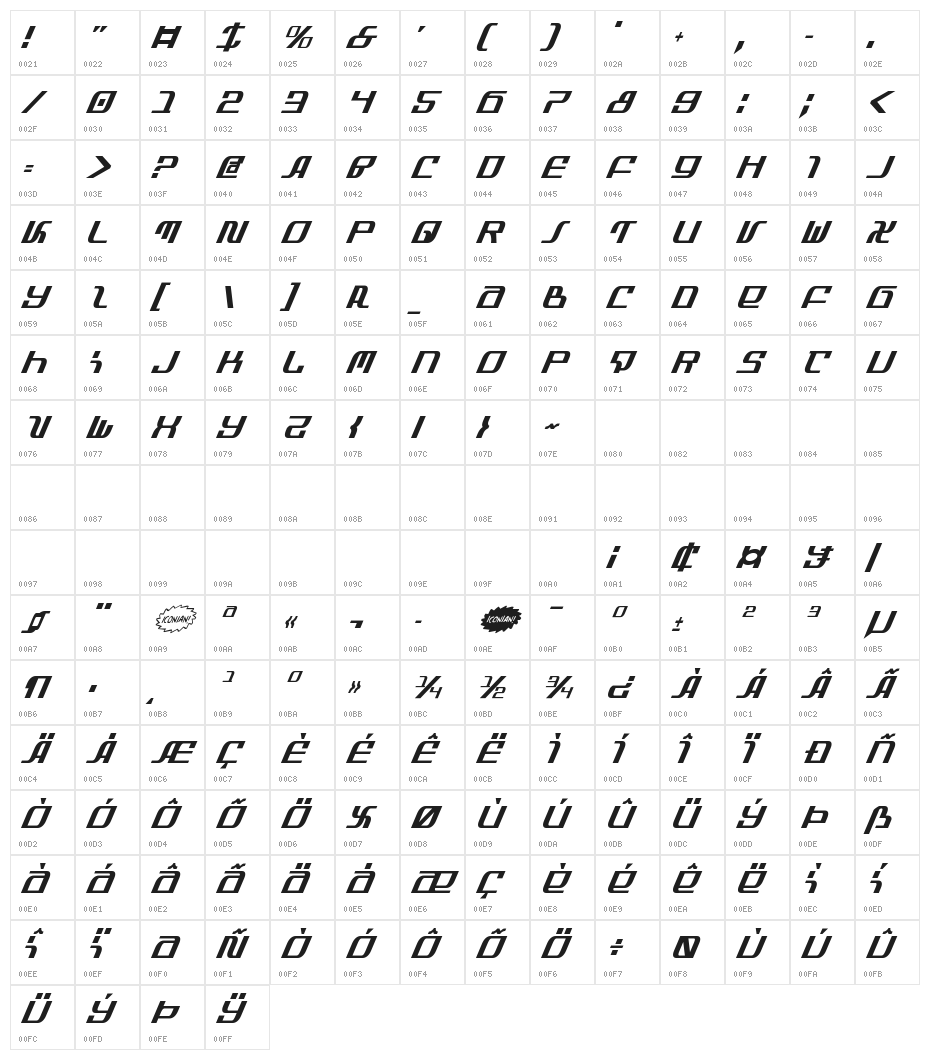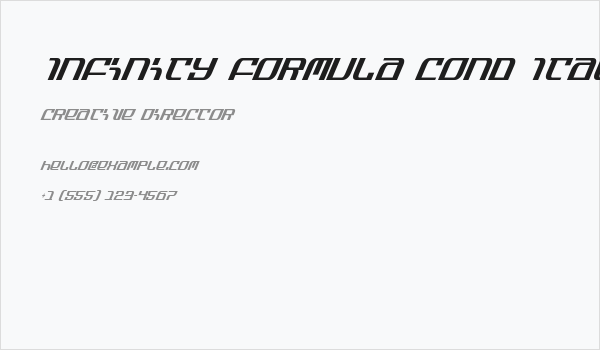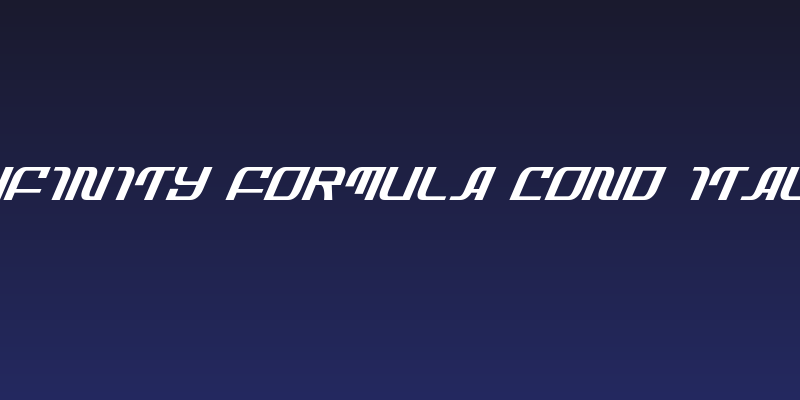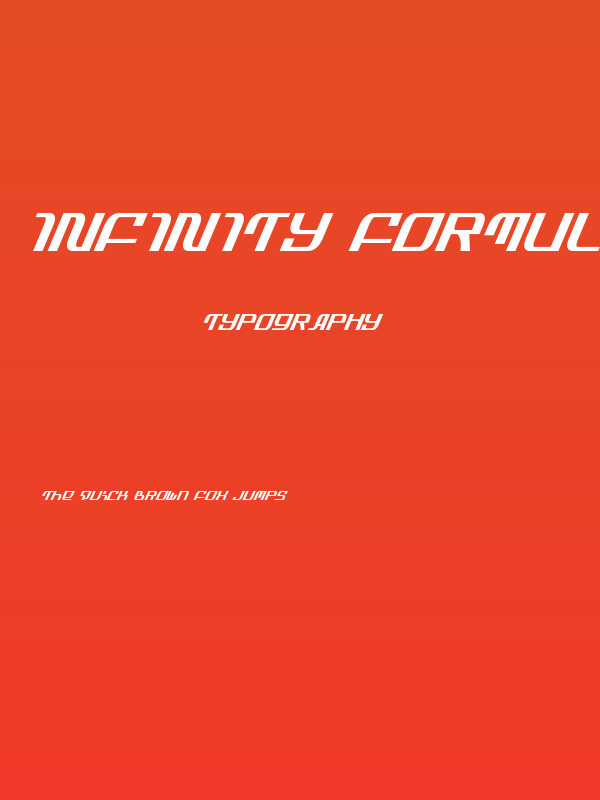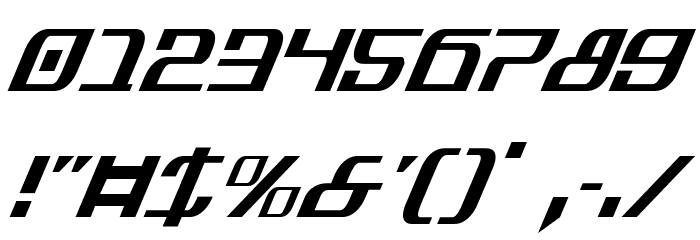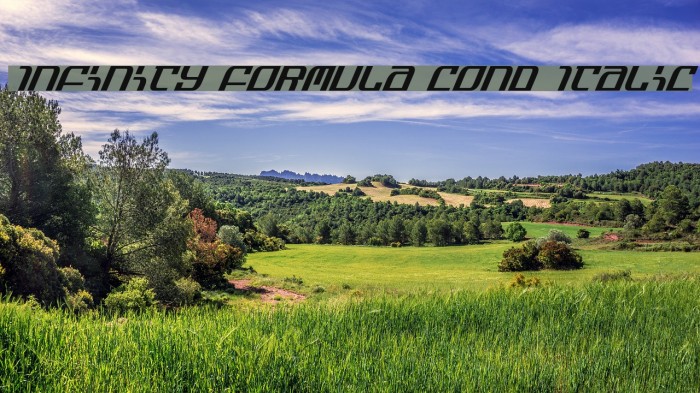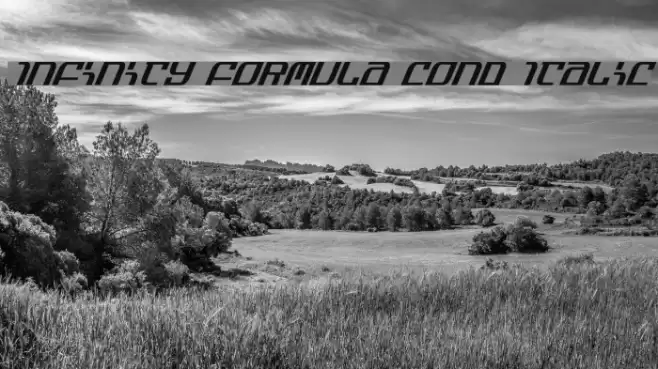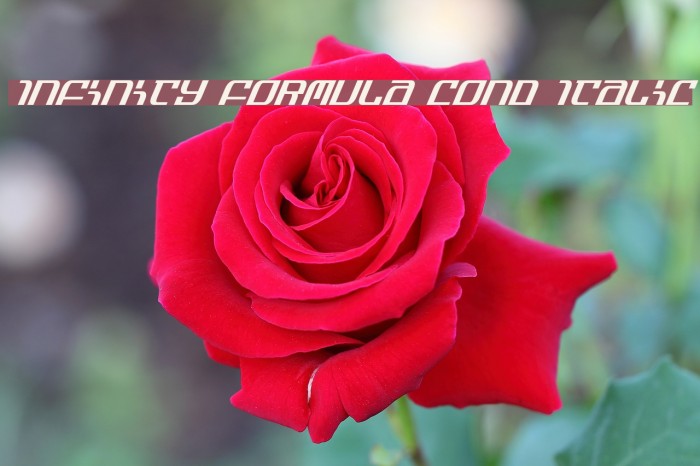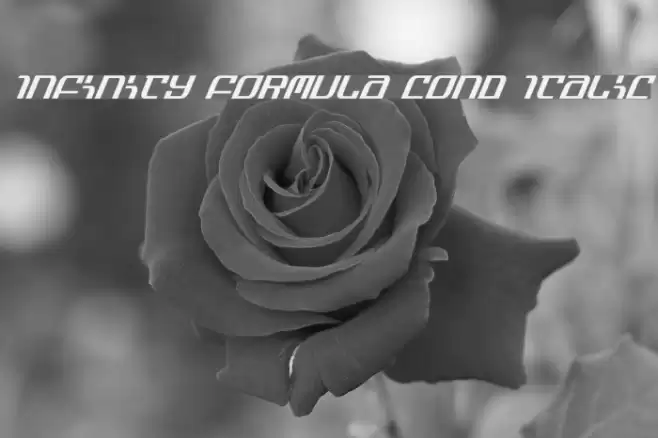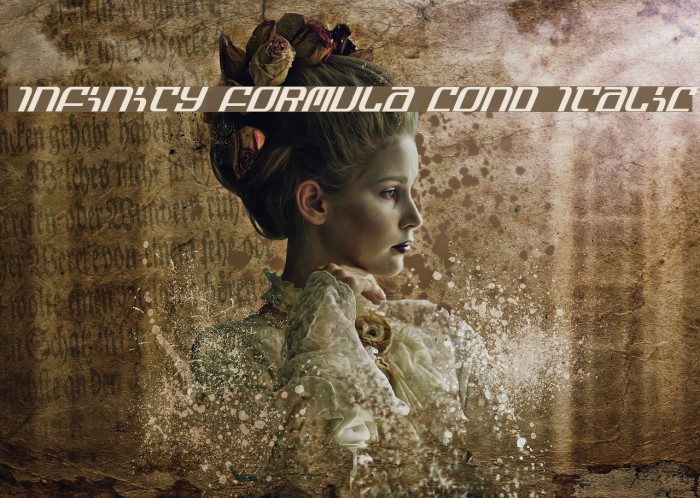
Infinity Formula Cond Italic Font
| Caz de utilizare | Logos, Headlines, Branding |
| Proiecte propuse | Ideal for branding, sports team logos, technology-related projects, and dynamic advertising campaigns. |